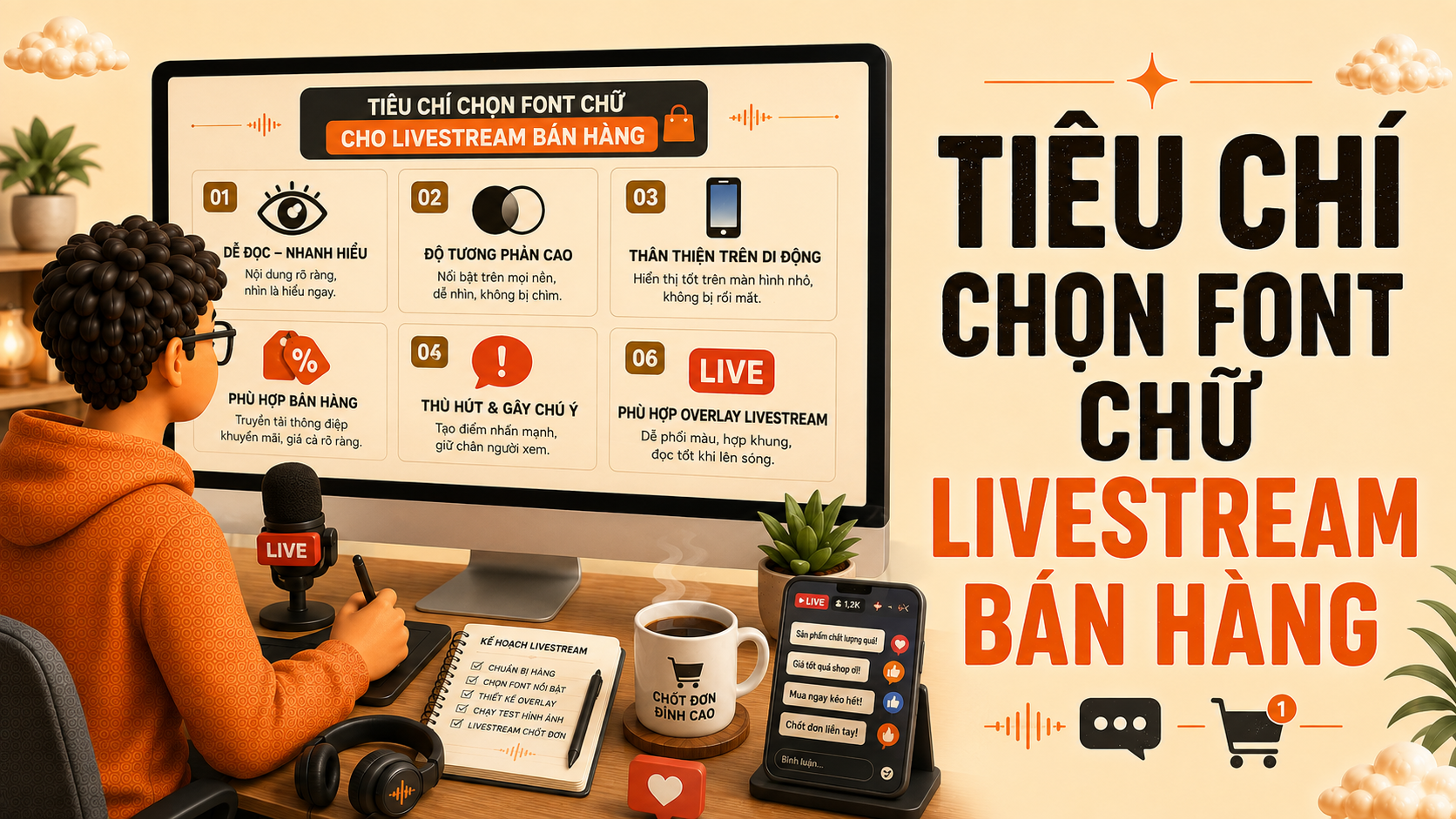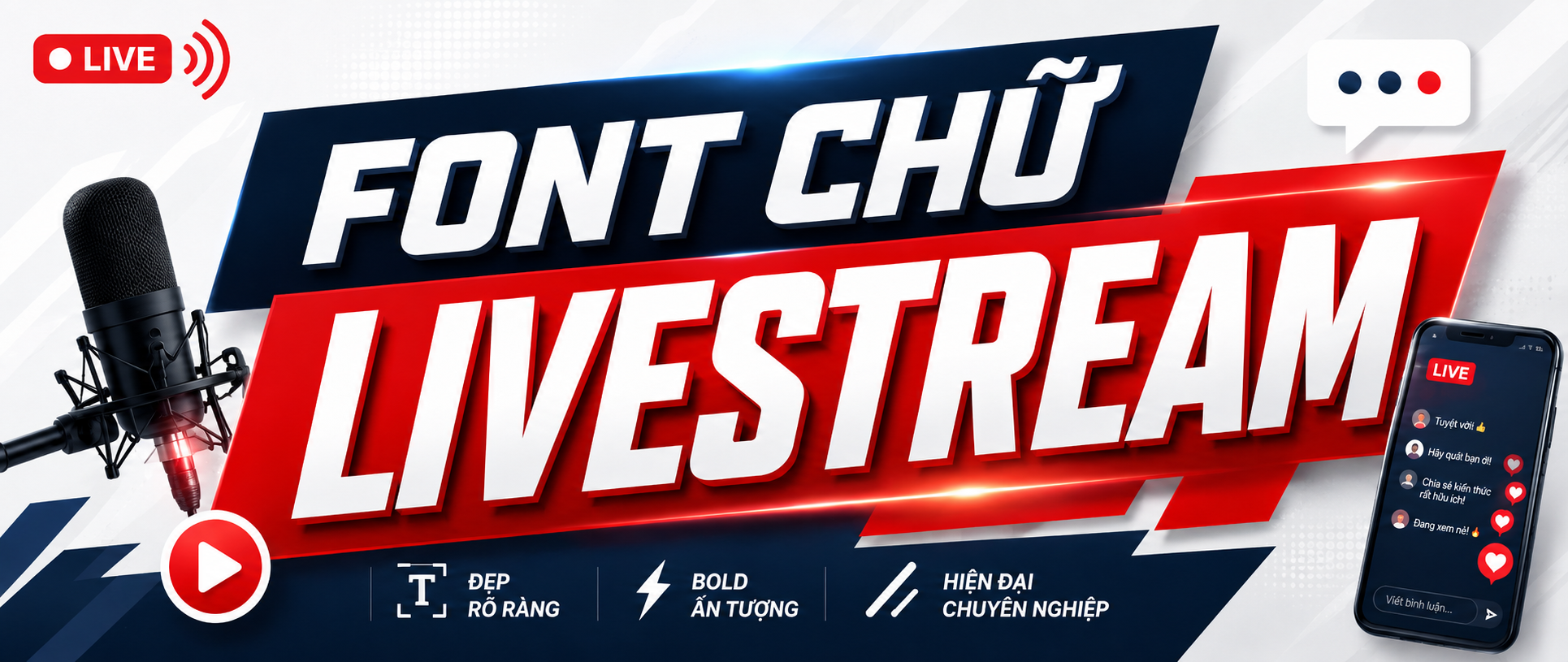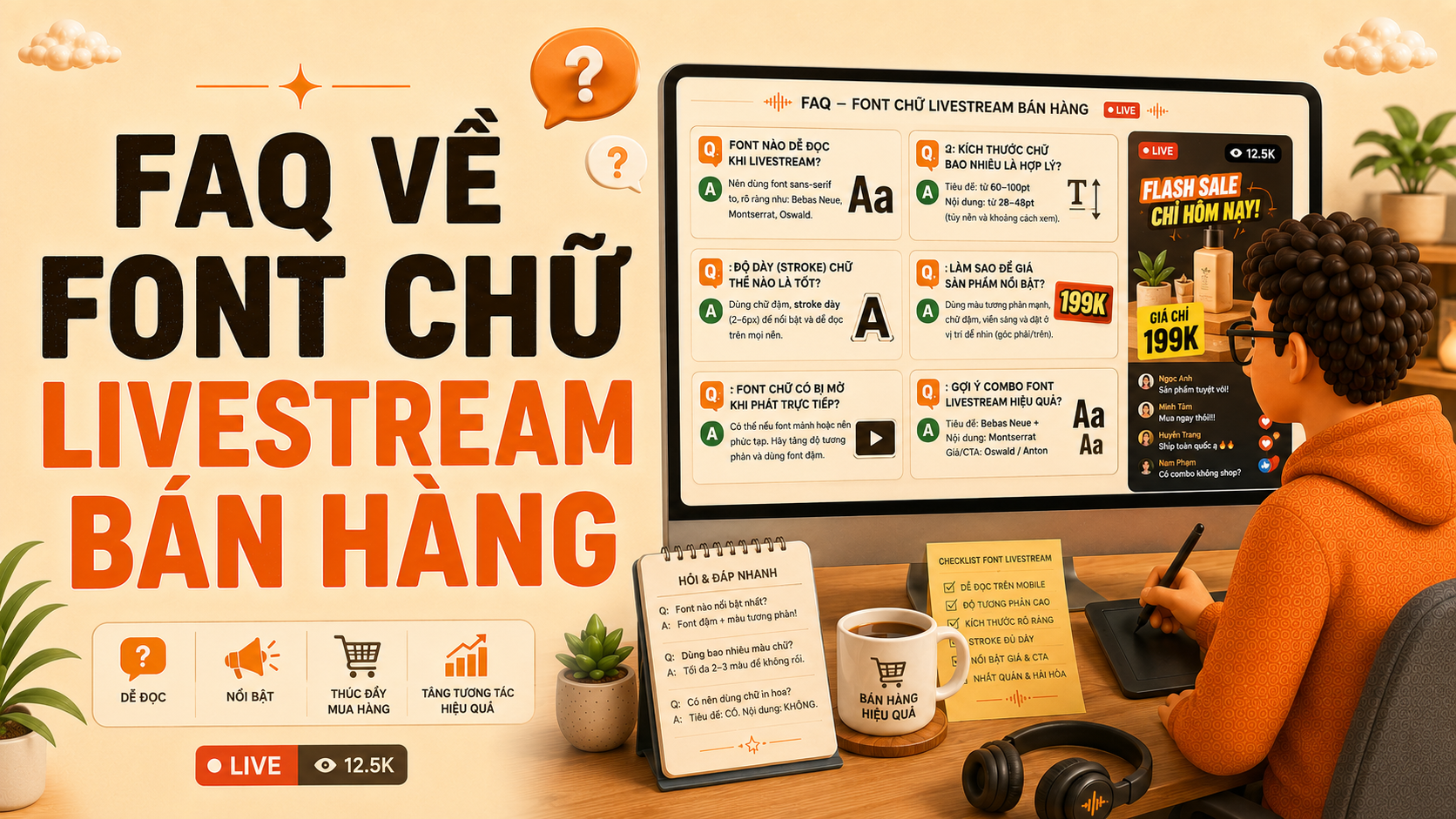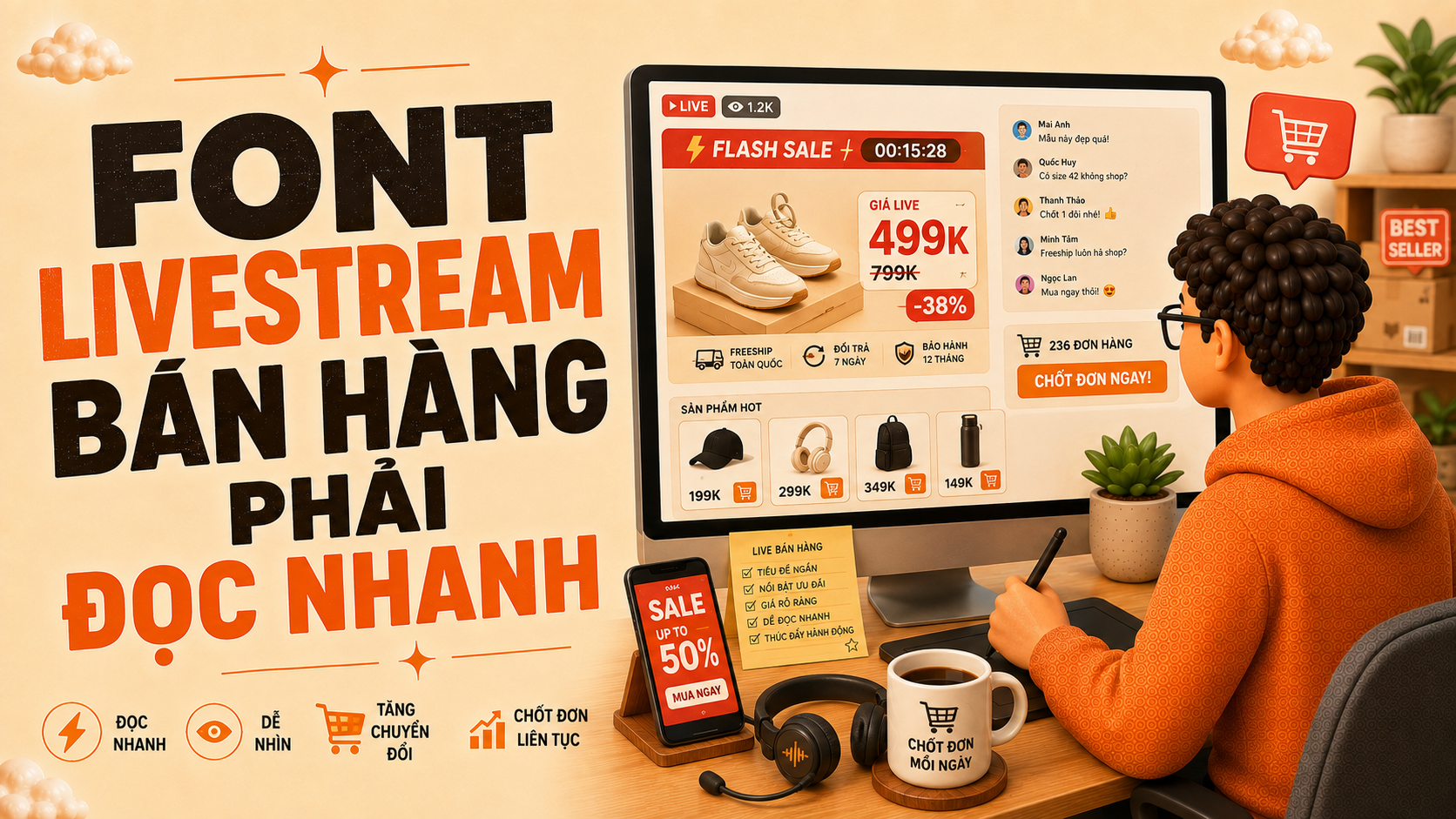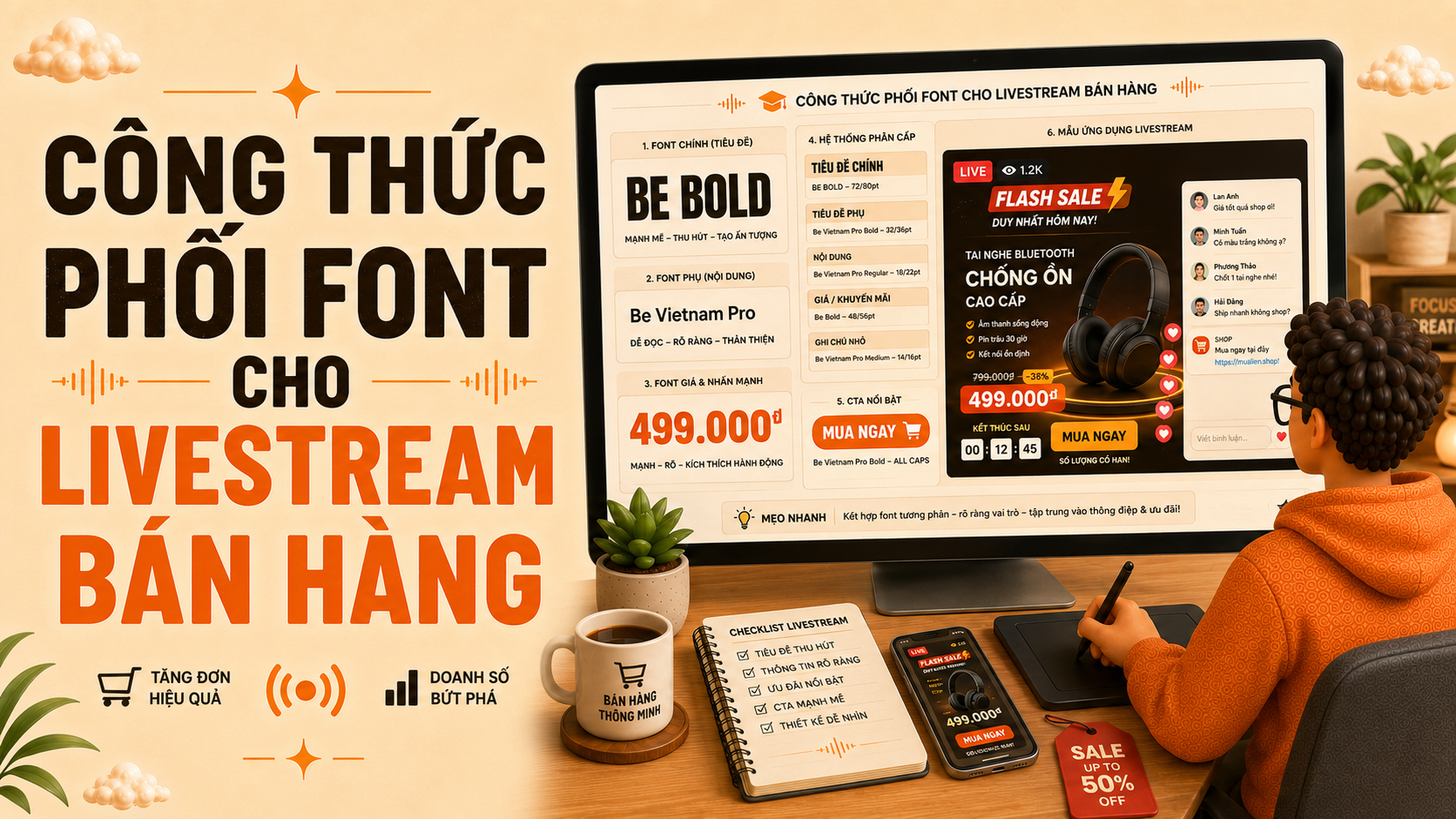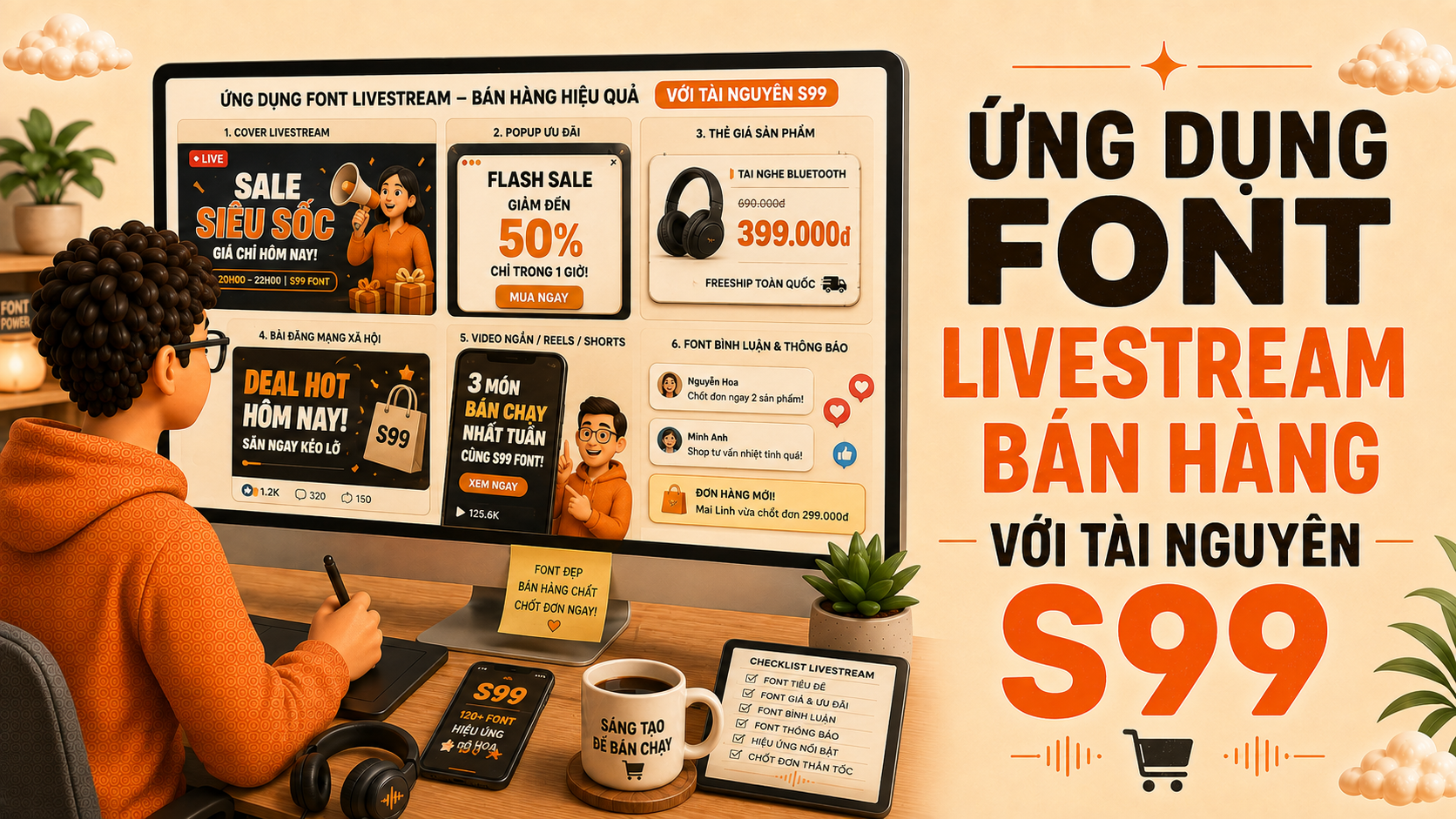
Font chữ livestream bán hàng: chọn font Việt hóa cho overlay, voucher và chốt đơn
Livestream bán hàng là nơi chữ phải làm việc rất nhanh. Người xem lướt qua màn hình nhỏ, nghe người bán nói, nhìn sản phẩm, đọc bình luận, so giá và quyết định đặt hàng chỉ trong vài giây. Vì vậy, font chữ livestream bán hàng không chỉ cần đẹp. Font phải rõ, có lực, hỗ trợ tiếng Việt tốt và giúp thông tin quan trọng như giá, mã giảm, số lượng, CTA nổi bật ngay lập tức.
Font livestream bán hàng phải đọc nhanh hơn poster thông thường
Poster có thể cho người xem dừng lại vài chục giây. Livestream thì khác. Màn hình luôn chuyển động, sản phẩm được cầm trên tay, bình luận chạy liên tục, biểu tượng thả tim che một phần khung hình và người xem có thể thoát bất cứ lúc nào. Nếu chữ khó đọc, thông tin ưu đãi sẽ bị trôi qua trước khi khách kịp phản ứng.
Một layout live tốt thường có các lớp chữ riêng: tiêu đề chương trình, tên sản phẩm, giá bán, giá gạch, mã voucher, số điện thoại hoặc cú pháp chốt đơn, thời gian ưu đãi, freeship, quà tặng và lời kêu gọi như bình luận mã sản phẩm hoặc bấm giỏ hàng. Font cho từng lớp không nên giống nhau hoàn toàn, nhưng cũng không được rối.
Với tiếng Việt, dấu chữ là điểm phải kiểm tra trước. Các cụm như giảm sốc, chốt đơn, miễn phí vận chuyển, đồng giá, xả kho, ưu đãi hôm nay, số lượng có hạn đều có dấu dày. Font lỗi dấu hoặc dấu quá sát thân chữ sẽ làm overlay nhìn kém chuyên nghiệp, nhất là khi phát trực tiếp ở chất lượng nén.
Tiêu chí chọn font chữ livestream bán hàng
Rõ trên mobile và nền video nhiều chi tiết
Phần lớn người xem livestream bằng điện thoại. Font cần đọc được khi thu nhỏ, khi đặt trên nền sản phẩm nhiều màu, khi bị nén chất lượng hoặc khi màn hình có nhiều bình luận. Font quá mảnh, quá bay hoặc khoảng cách chữ quá chặt thường không phù hợp làm chữ chính.
Số, giá tiền và phần trăm giảm giá phải nổi bật
Livestream bán hàng phụ thuộc rất nhiều vào con số: 99K, 199K, giảm 50%, mua 2 tặng 1, còn 20 suất, voucher 30K. Hãy chọn font có số rõ, thân chữ chắc và độ tương phản tốt để giá không bị nhòe khi đặt trong badge hoặc khung sale.
Dấu tiếng Việt ổn định
Font Việt hóa tốt giúp các từ có dấu lên đều, không bị lệch, không vỡ và không chen vào dòng trên. Đây là yếu tố đặc biệt quan trọng nếu bạn dùng chữ lớn trong thumbnail, overlay giá hoặc banner ghim đầu live.
Phù hợp ngành hàng
Livestream mỹ phẩm cần cảm giác sạch, đẹp, sang. Livestream đồ ăn cần thân thiện và ngon mắt. Livestream công nghệ cần gọn, hiện đại. Livestream xả kho cần mạnh và cấp bách. Chọn đúng font sẽ giúp khách hiểu tinh thần thương hiệu trước cả khi đọc hết nội dung.
Dễ phối với màu sale và khung overlay
Các màu thường gặp trong livestream là đỏ, vàng, cam, đen, trắng, hồng, xanh mint hoặc xanh công nghệ. Font cần đủ rõ khi đặt trên nút, tem sale, bảng giá, lower-third, sticker hoặc khung sản phẩm. Nếu font chỉ đẹp khi đứng một mình, chưa chắc đã dùng tốt khi lên live.
Font mạnh cho flash sale, giá sốc và mã voucher
Nhóm font display mạnh phù hợp với các phần cần kéo mắt ngay: flash sale, giá sốc, voucher, đồng giá, xả kho, deal cuối live, săn mã, chốt đơn nhanh. Đây là nhóm nên dùng cho headline ngắn, badge sale và thumbnail trước giờ live.
Khi dùng nhóm này, hãy giữ câu chữ thật ngắn. Các cụm như Flash Sale 20h, Deal sốc hôm nay, Voucher 50K, Chốt đơn ngay, Mua 1 tặng 1 sẽ hiệu quả hơn đoạn dài. Nếu cần ghi điều kiện áp dụng, thời gian hoặc mô tả sản phẩm, hãy chuyển sang font sans-serif rõ ở nhóm tiếp theo.
Font sans-serif rõ cho overlay, bảng giá và nội dung chốt đơn
Overlay livestream cần một nhóm font nền thật chắc. Đây là font dùng cho tên sản phẩm, size, màu, mã hàng, cú pháp bình luận, bảng giá, thông tin freeship, hotline, địa chỉ shop và hướng dẫn đặt hàng. Nhóm sans-serif rõ giúp khách đọc nhanh mà không phải căng mắt.
Nhóm này có thể dùng lâu dài cho nhiều buổi live khác nhau. Bạn có thể đặt font đậm cho giá, semibold cho tên sản phẩm và regular cho mô tả. Cách này giúp layout giữ được trật tự, đặc biệt khi mỗi buổi live có hàng chục sản phẩm cần thay nội dung liên tục.
Font sang cho livestream thời trang, mỹ phẩm và trang sức